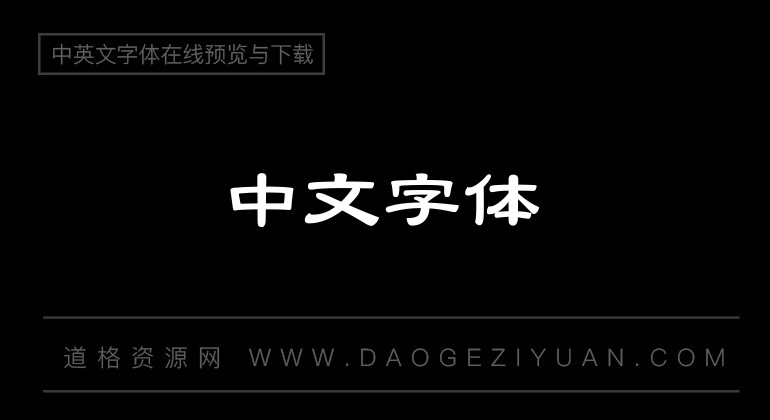
華康唐風隸W5是一款隸書字體,採用典雅、古典、穩重的風格,是仿宋體的一種細膩的隸書字體。它的特點是字形規整,筆劃細膩,結構嚴謹,筆劃精緻,曲線流暢,線條細膩,比例協調,符號簡潔,較宋體更具有古典的風采。它適用於各種類型的文字,尤其適合用於精美的報紙、書刊、圖書、雜誌等印刷品,是文字排版的首選字體。內容介紹
華康唐風隸W5是一款非常不錯的手寫藝術字體,具有很好的視覺感,適合於文化類的宣傳設計、商業類品牌的廣告和產品包裝設計以及個性化文字排版等較多場景。